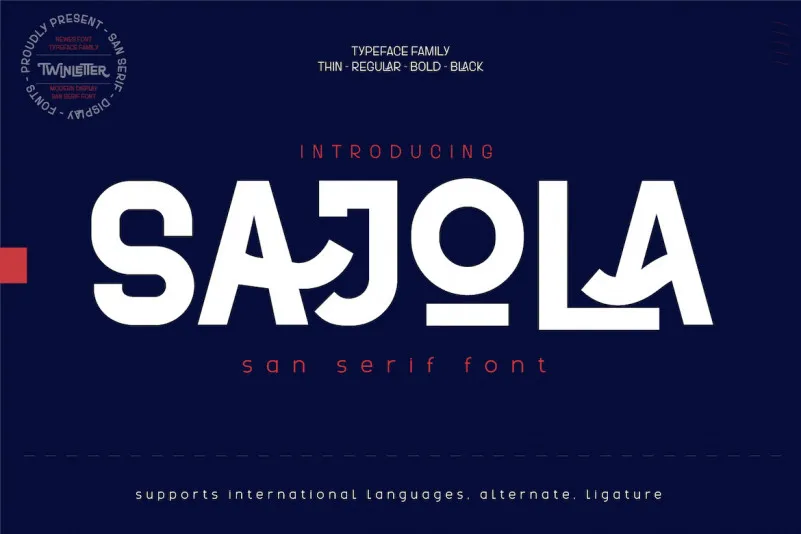
Sajola Font – Fonte Grátis
Sajola Font
A ‘Sajola Font’ é uma escolha perfeita para quem busca um estilo simples e elegante na tipografia sem ser minimalista excessivamente. Originária do design atento de twinletter, essa fonte sans serif traz uma leveza que se torna uma ótima companheira em projetos digitais variados: desde sites profissionais até designs mais divertidos. Seus traços finos e linhas levemente curvadas criam um equilíbrio perfeito sem perder o toque moderno e contemporâneo que a fonte sem serif é conhecida por ter. O resultado é uma opção ideal para designers em busca de um visual clean e sofisticado, que não se esquece do charme mais suave da tipografia moderna. Instale ‘Sajola’ hoje e experimente como ela pode revolucionar seu próximo projeto.